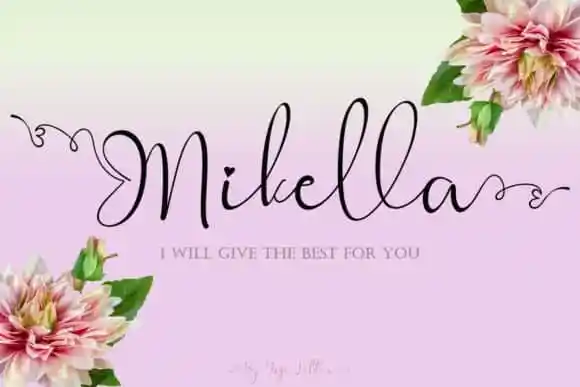
Mikella Calligraphy Font – Download Grátis
A Mikella Calligraphy Font é uma escolha perfeita para quem procura elegância e sofisticação em seu trabalho gráfico. Feita pelo designer yogaletter6, esta font se destaca como um tipo moderno com traços manuscritos, sendo elegantemente bela além de única e altamente funcional. Ideal para aplicar em trabalhos de casamento, seja para branding, cabeçalhos, convites, assinaturas, etiquetas ou logotipos, esta font irá dar um toque especial a qualquer projeto. A Mikella Calligraphy Font é uma opção perfeita para quem valoriza tanto o design quanto a funcionalidade, proporcionando beleza e versatilidade sem comprometer a qualidade do trabalho.